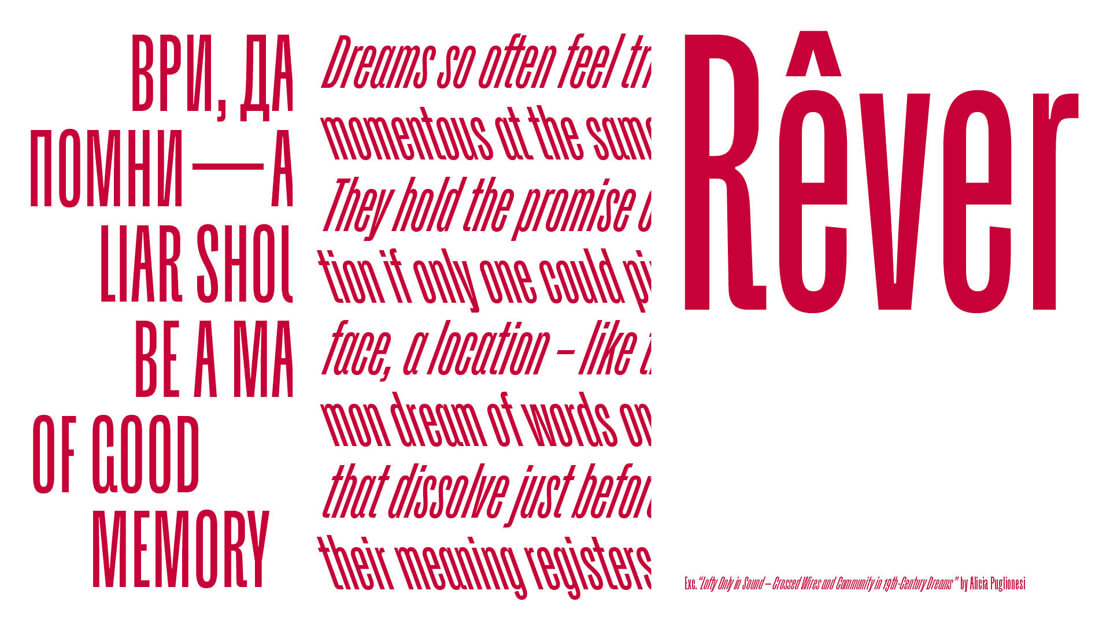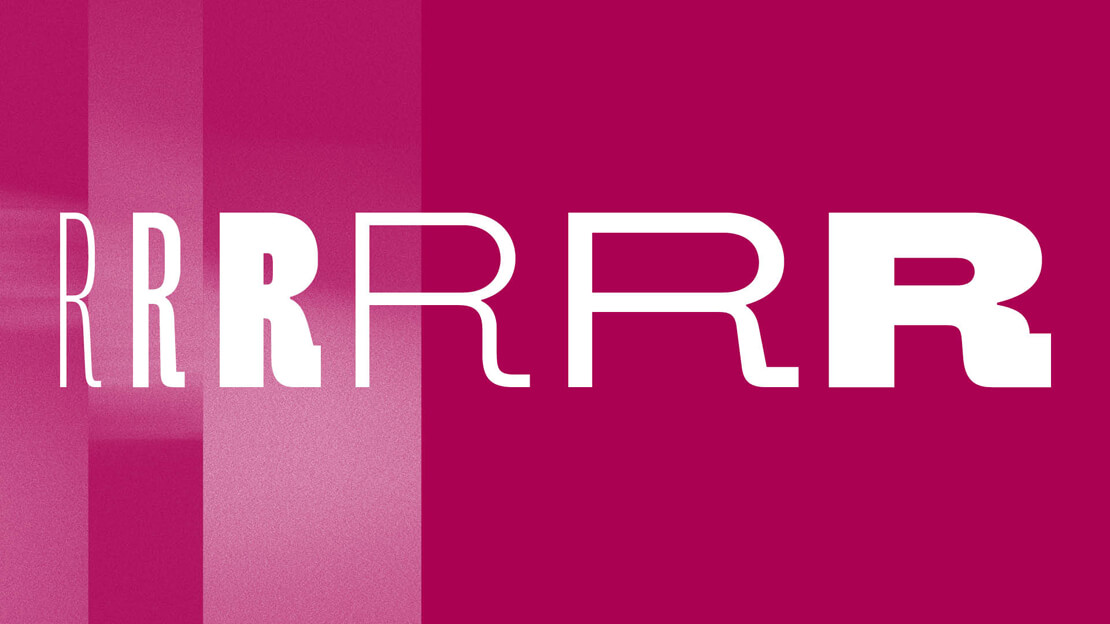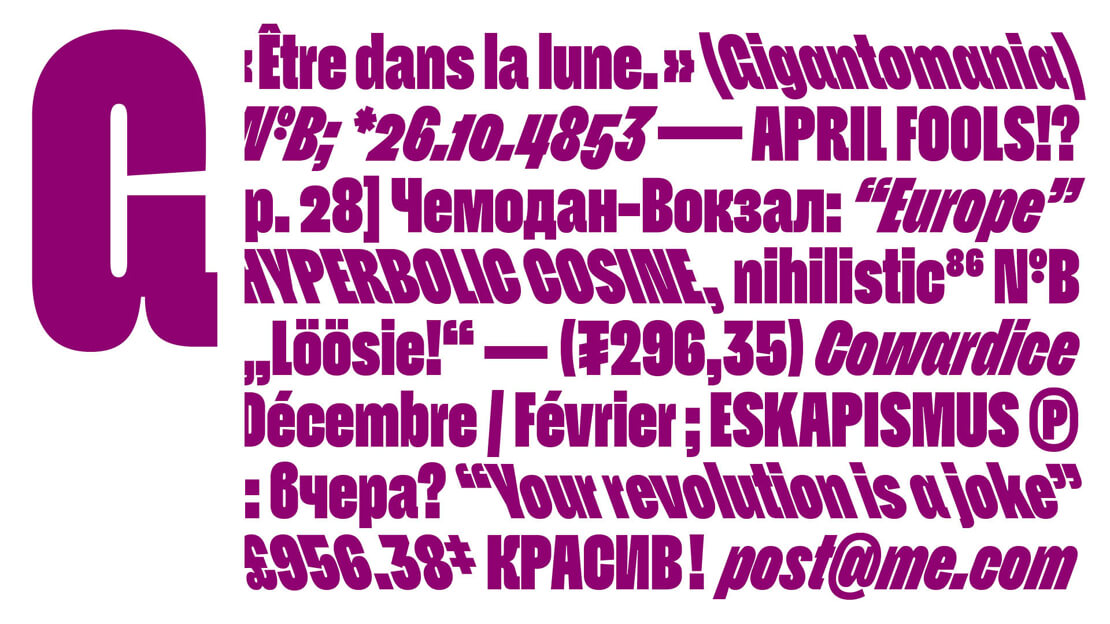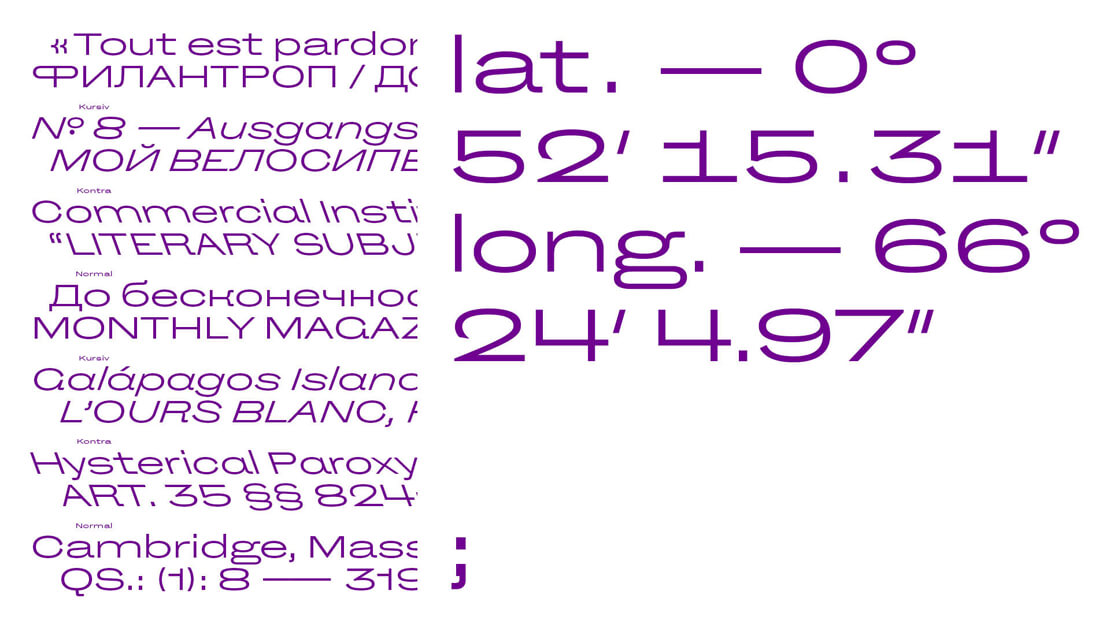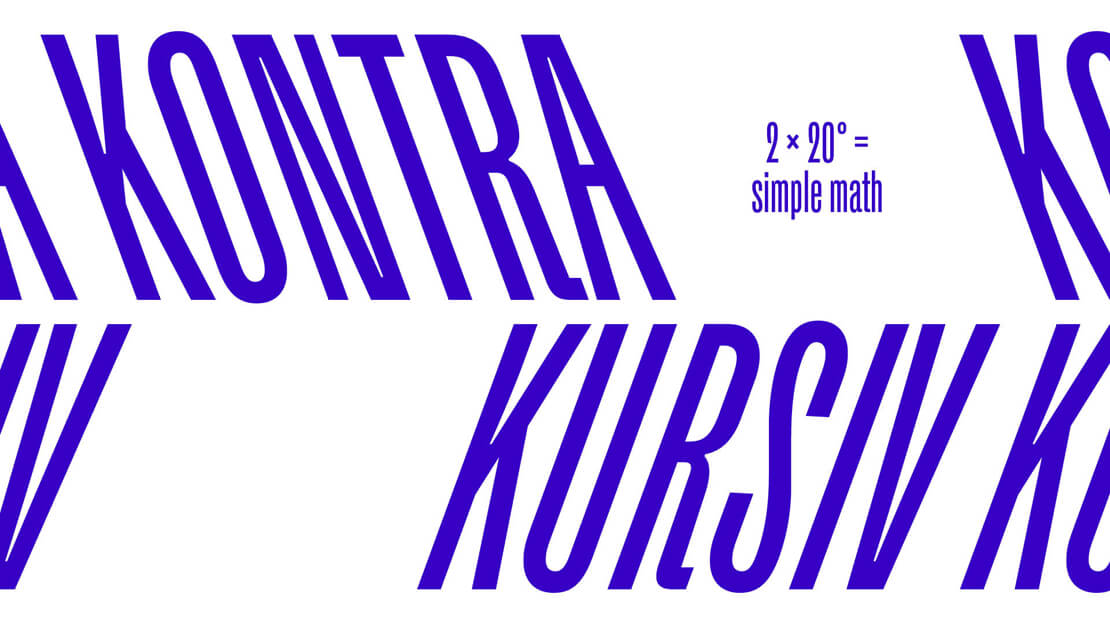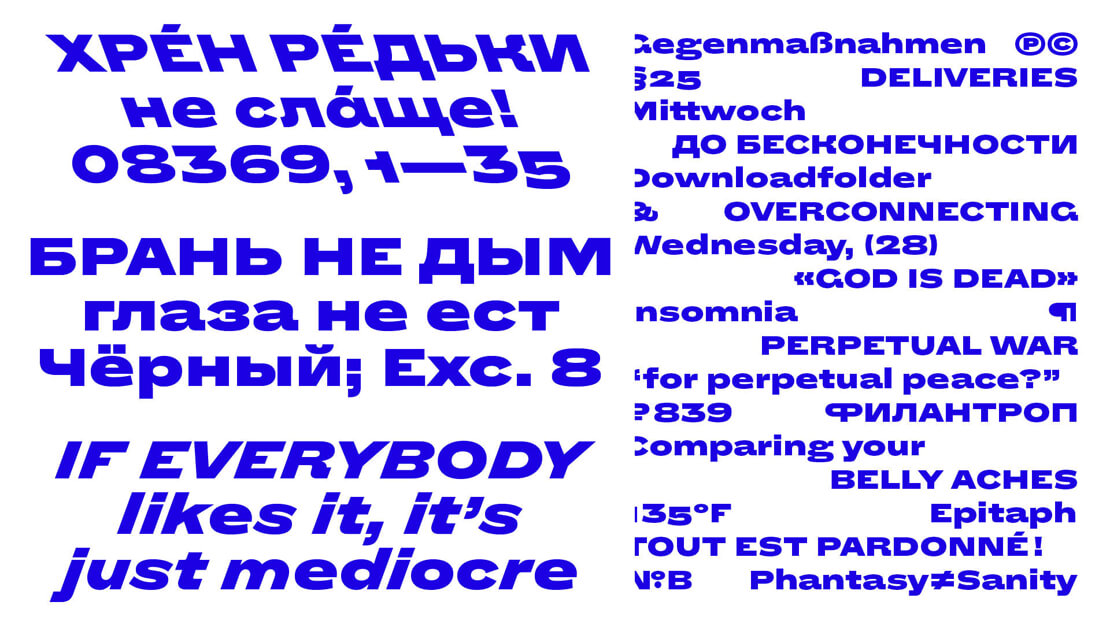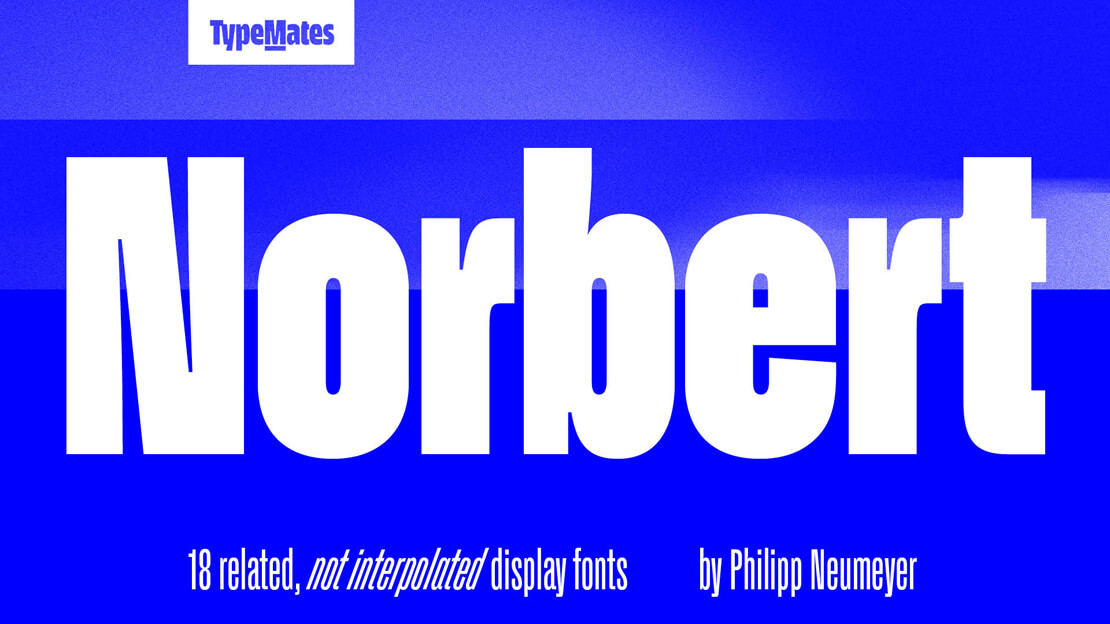
»Norbert« bei TypeMates erschienen
Inspiriert von den gegensätzlichen Gestaltungsstilen früherer Schriftfamilien aus dem Bleisatz, spielt Norbert mit Widersprüchen und bedient sich dabei der Extreme. Das Ergebnis ist eine moderne Grotesk-Schriftart.
»Norbert« denkt in Extremen: Schmal oder Breit, Kursiv oder Kontra. Dabei verzichtet die Schriftfamilie absichtlich auf eine reguläre Weite oder interpolierte Zwischengewichte.
»Norbert ist ein Freigeist, der sich nicht um Regeln schert, sondern lieber mit individuell gezeichneten Schriftschnitten glänzt und seine Stärke und Vielseitigkeit in Marken und Editorial Projekte einbringt.«, erklärt Philipp Neumeyer. »Norbert ist, wie er ist: Kein Arbeitstier, aber eine Schrift, die sich je nach Anlass zart und edel oder auch grob und rau zeigen kann. Lass dich überraschen.«
Bei der Gestaltung der Schriftfamilie ließ sich der Type-Designer von kyrillischen Bleilettern an einem Gebäude in St. Petersburg inspirieren. Deshalb kann »Norbert« auch fließend Russisch. Außerdem enthält die Schrift eine umfangreiche Sammlung von Pfeilen, die sich vielfältig verwenden lassen.